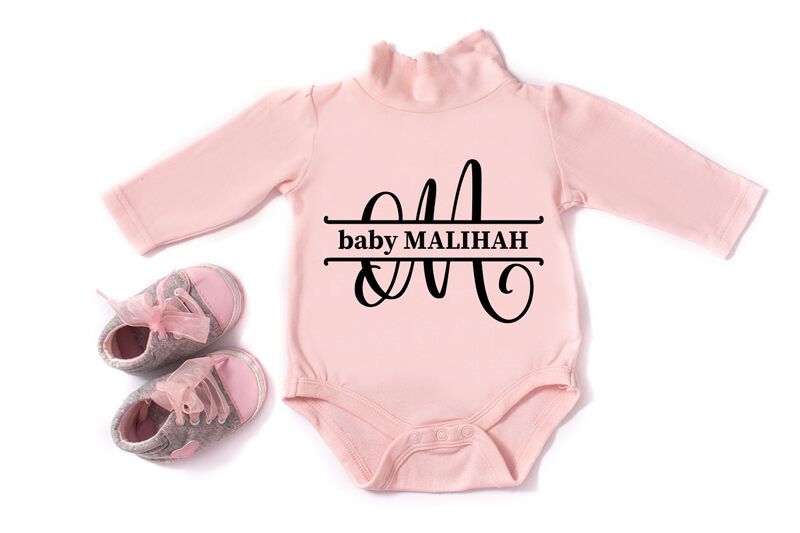
Glam
Glam par Abo Daniel est une police d'affichage décorative gratuite, caractérisée par ses longues boucles et ses courbes fluides rappelant l'écriture manuscrite. Ses lettres se déploient en arcs élégants, agrémentées de larges fioritures horizontales qui donnent au design un rythme ornemental sophistiqué.
Glam est une police gratuite idéale pour les faire-part de mariage, les logos, l'image de marque, les citations sur les réseaux sociaux, le packaging et les titres décoratifs. Elle convient parfaitement aux mises en page nécessitant un style tout en courbes, car ses lignes étendues créent un accent raffiné sans alourdir la composition.